이 글에서는 폰트 찾기의 중요성과 이미지로 폰트를 빠르게 찾는 방법을 소개합니다. 한글과 영문 폰트 모두 효율적으로 찾는 팁을 공유하며, 여러분의 디자인 작업을 한층 수월하게 만들어 드릴 것입니다.
폰트 찾기란?
폰트 찾기는 우리가 원하는 글꼴을 식별하는 과정입니다. 텍스트 디자인에서 폰트는 기본적인 요소 중 하나죠. 적절한 폰트를 선택하는 것이 디자인의 전체적인 분위기를 결정짓는 데 매우 중요합니다. 예를 들어, 뉴스 기사에는 신뢰감을 주는 세리프 계열의 폰트가 많이 사용되고, 개인 블로그에는 감각적이고 자유로운 느낌을 주는 산세리프 폰트가 적합하죠. 폰트 찾기를 통해 적합한 폰트를 찾는 것은 결과적으로 프로젝트의 성공을 위한 초석이 됩니다. 그럼, 폰트를 어떻게 쉽게 찾을 수 있을까요?
이미지로 폰트를 찾는 방법은 특히 유용합니다. 예를 들어, 마음에 드는 포스터나 웹사이트 디자인을 보았을 때, 글씨체가 궁금해지는 순간이 있습니다. 이럴 때에 이미지로 폰트 찾기를 활용하면 좋습니다. 특정 글꼴이 어떤 것인지 정확하게 알아내는 것은 정말 흥미로운 일이 아닐 수 없습니다. 검색 엔진이나 특화된 웹사이트를 통해 이미지 업로드만으로도 쉽게 찾아낼 수 있거든요. 이렇게 폰트를 빠르게 확인하면, 영감을 얻는 데 큰 도움이 될 것입니다.
하지만 모든 폰트를 찾는 것이 항상 쉽지는 않습니다. 특히 한글과 영문 폰트는 다양한 옵션이 존재해 선택의 폭이 넓습니다. 한글 폰트 찾기는 특히 더 복잡할 수 있는데, 한국어의 특성상 다양한 굴림체와 바탕체가 존재하니 사용자마다 선호하는 스타일이 다를 수 있습니다. 내 스타일에 맞는 폰트를 찾는 것은 시간이 걸릴 수 있지만, 그 과정이 충분히 즐거울 수 있도록 노력해보세요. 너무 다양한 옵션 가운데 자신만의 취향을 확인하는 재미를 느낄 수 있을 것입니다!
이미지로 폰트 찾기 방법
이미지를 이용한 폰트 찾기는 간단하면서도 효과적인 방법입니다. 먼저, 원하는 글꼴이 있는 이미지를 준비해야 합니다. 이때 이미지의 질이 중요하죠. 글자가 선명하고 깨끗하게 보이는 이미지를 선택해야 정확도가 높아집니다. 그 후, 폰트 찾기 웹사이트나 애플리케이션을 이용하여 이미지를 업로드하면 됩니다. 이러한 작업은 클릭 몇 번으로 쉽게 이루어질 수 있습니다. 이처럼 기술이 발전한 덕분에 우리는 편리하게 디자인 작업을 이어나갈 수 있습니다.
여기서 몇 가지 유용한 웹사이트를 소개합니다. 'WhatTheFont'와 같은 사이트는 업로드된 이미지를 분석하여 유사한 폰트를 추천합니다. 사용법은 간단하기 때문에, 처음 이용하는 분들도 쉽게 접근할 수 있습니다. 또 다른 대표적인 사이트인 'Identifont'는 글꼴의 형태와 특징을 기반으로 폰트를 찾을 수 있는 방법을 제공합니다. 각각의 사이트가 제공하는 정보와 추천은 다를 수 있으니 여러 번 비교해 보는 것도 좋습니다. 이렇게 이미지로 폰트 찾기를 하다 보면, 당신의 라이브러리도 점점 풍부해질 것입니다.
폰트 찾기 성공 사례
많은 사람들이 이미지로 폰트를 찾아 디자인 프로젝트에 활용한 경험이 있습니다. 예를 들어, 한 커플이 결혼식 초대장을 디자인하기 위해 인스타그램에서 영감을 얻었습니다. 저희는 그 초대장에 쓰인 멋진 폰트를 폰트 찾기 서비스를 통해 찾아냈어요. 이 폰트를 사용함으로써 그들의 초대장은 더욱 특별해졌죠. 이렇게 간단한 기술이 누군가의 특별한 순간을 더욱 빛나게 하는 데 기여할 수 있습니다.
또 다른 사례로, 한 디자인 학원에서는 학생들이 유명 광고 포스터에서 발견한 폰트를 찾기 위해 영문 폰트 찾기 활동을 진행했습니다. 학생들은 각자의 감각으로 다양한 글꼴을 읽고 분석하여, 자신들의 프로젝트에 적용하였습니다. 이러한 과정은 디자인 실력을 향상시키는 데 매우 유익했습니다. 시각적인 요소를 이해하고 직접 활용하는 재미를 느꼈다고 말씀하셨습니다. 이처럼 폰트 찾기는 디자인 작업에 실질적인 도움을 줄 수 있는 요인입니다.
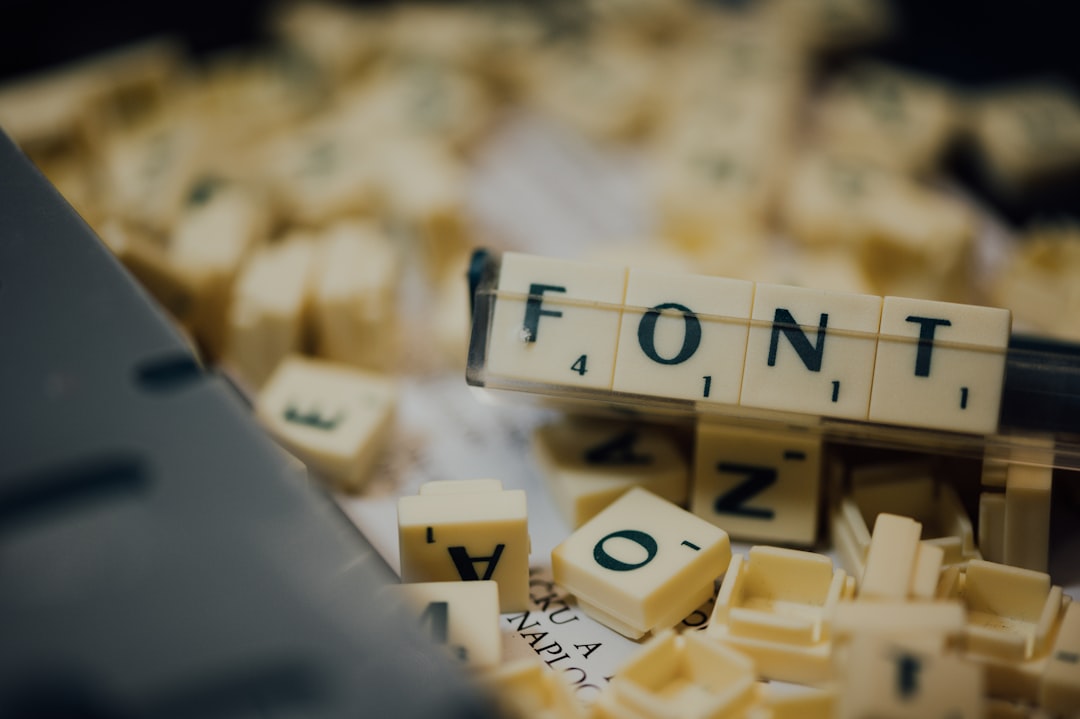
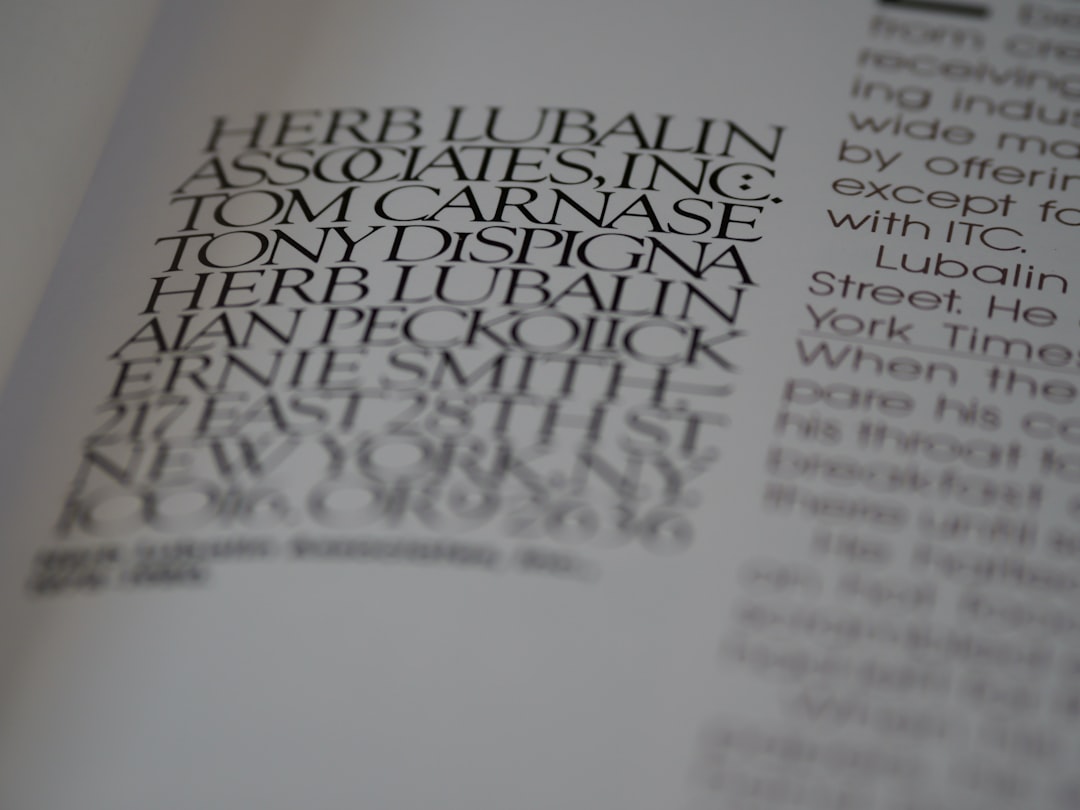
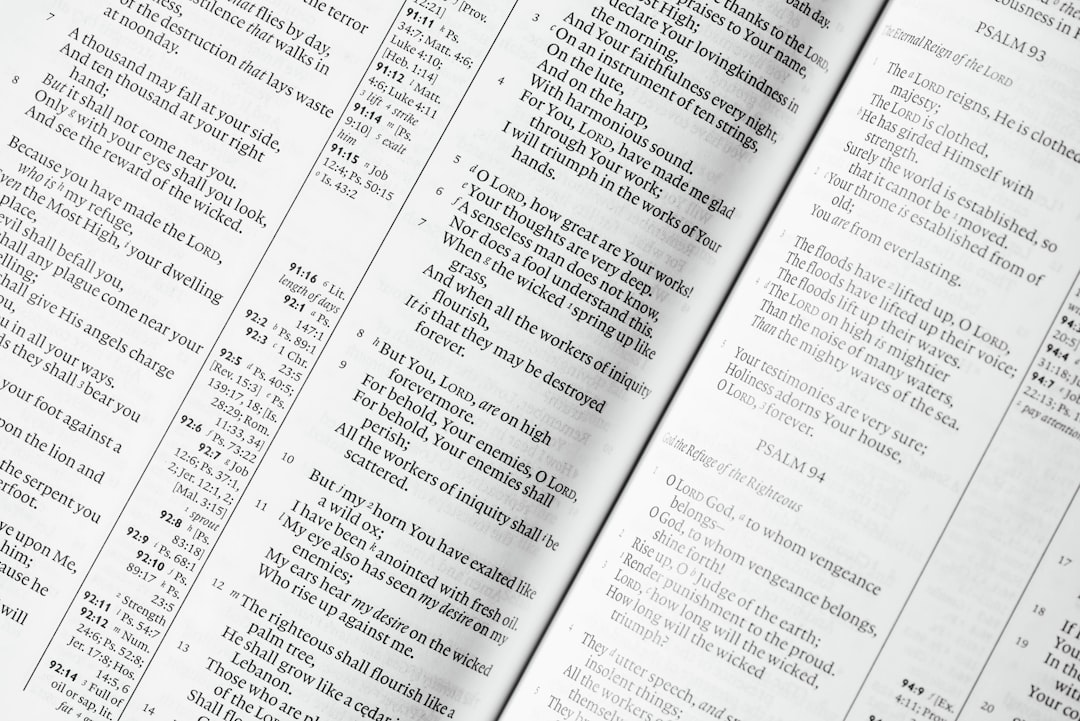
| 웹사이트 | 특징 |
|---|---|
| WhatTheFont | 이미지 기반 폰트 추천 |
| Identifont | 질문 기반 폰트 추천 |
결론
폰트 찾기는 이제 막 시작된 탐험과도 같습니다. 디자인의 중요한 요소인 폰트를 효율적으로 찾는 방법은 우리의 창의성을 더욱 드높이고 디자인 작업을 한층 쉽고 즐겁게 만들어 줍니다. 이제, 여러 웹사이트와 앱을 통해 폰트 찾기를 즐기기 시작해 보세요. 마음에 드는 폰트를 찾은 순간, 여러분의 디자인 작업이 새롭게 찬란히 빛날 것입니다!
자주 묻는 질문
1. 이미지로 폰트를 어떻게 찾나요?
이미지를 업로드할 수 있는 웹사이트에 접속하여 원하는 이미지를 업로드하면, 자동으로 유사한 폰트를 추천해 줍니다.
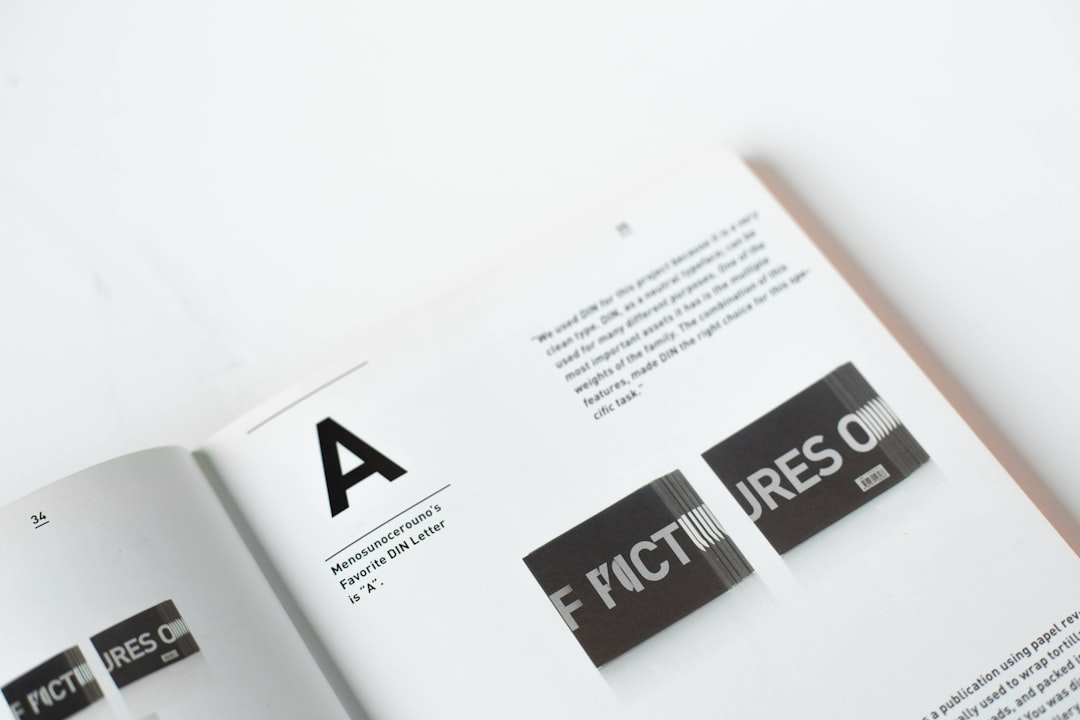
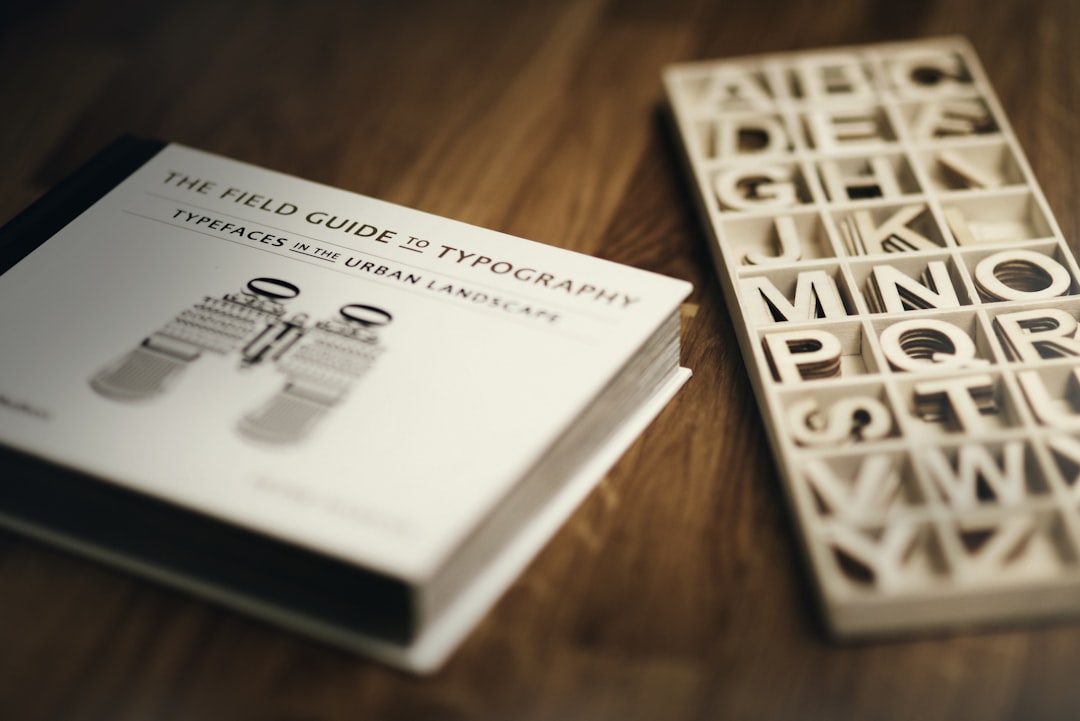
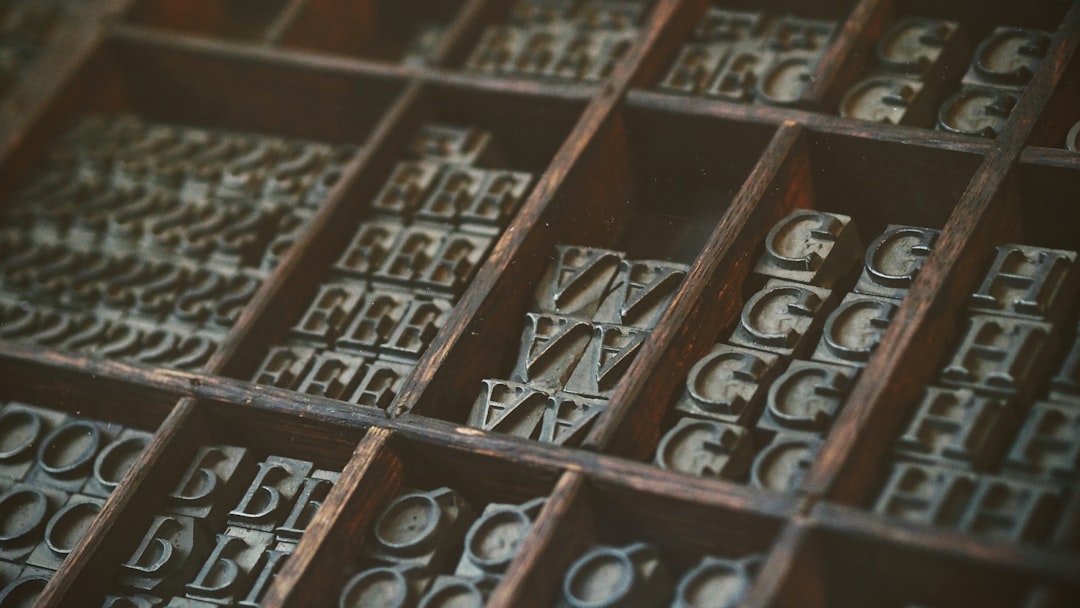
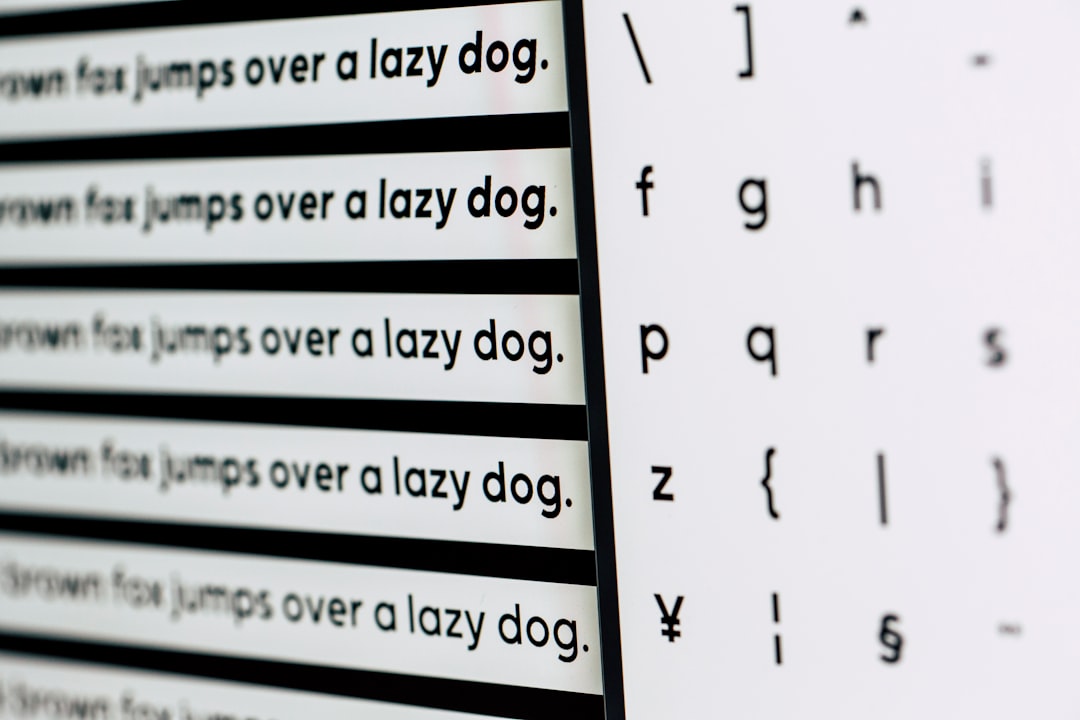
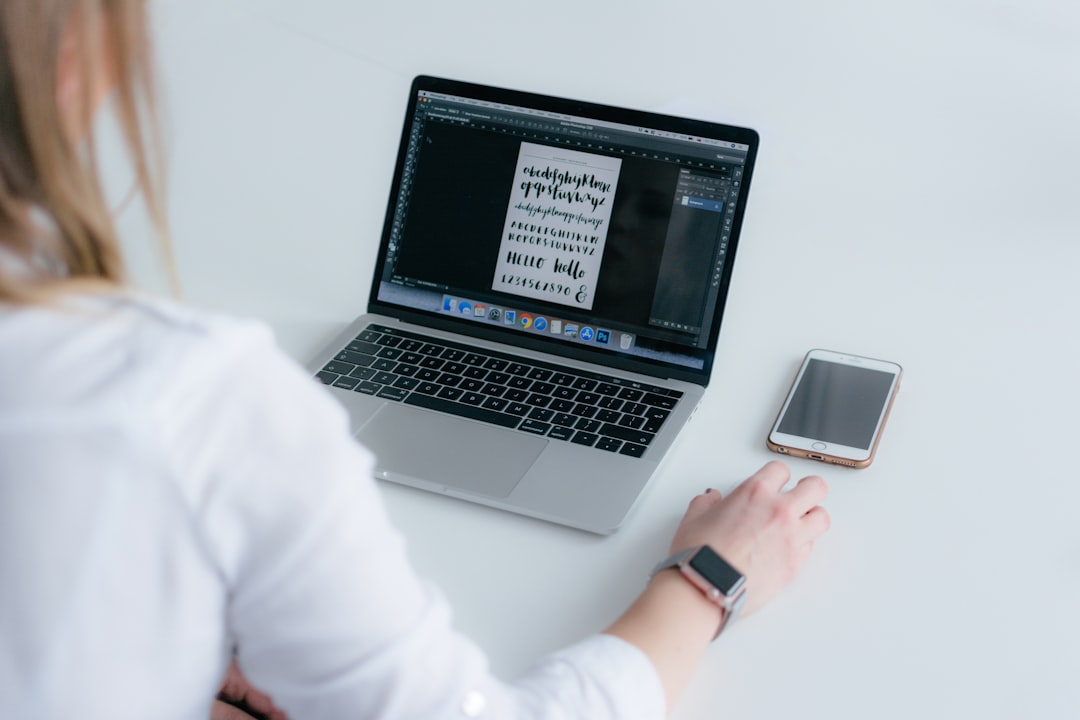
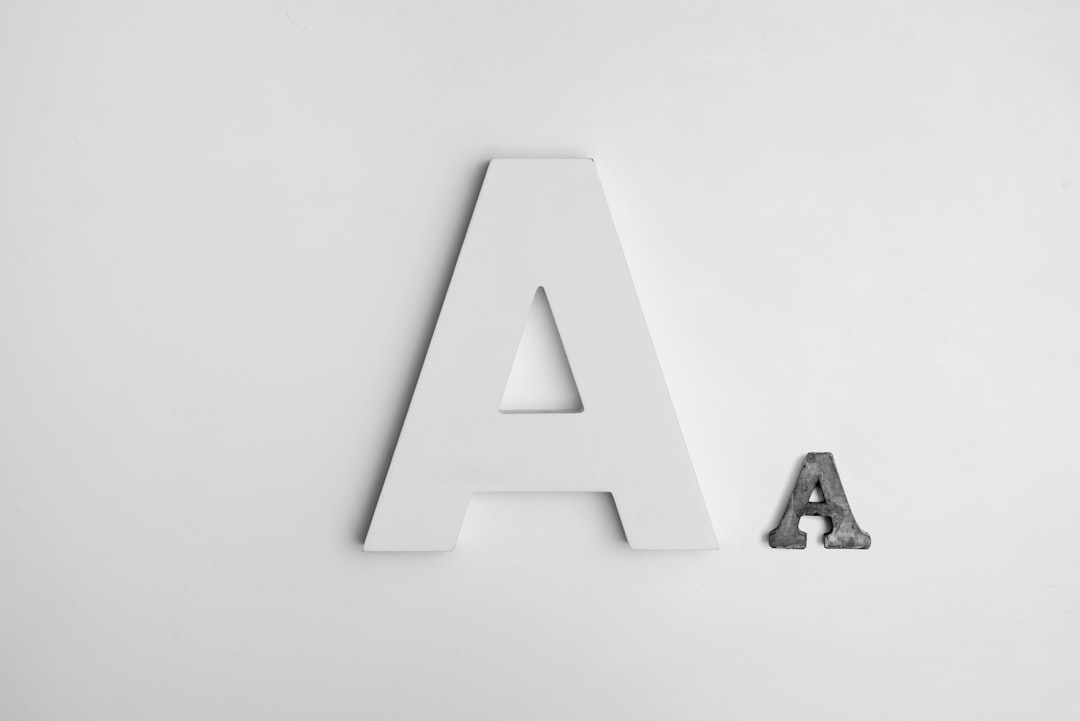
2. 한글 폰트는 어디에서 쉽게 찾을 수 있나요?
한글 폰트는 여러 사이트에서 제공하며, 각기 다른 스타일을 비교해 보면서 선택할 수 있습니다.
3. 영문 폰트 찾기가 어려운 이유는?
영문 폰트는 다양성이 크고, 비슷한 스타일이 많기 때문에 비교적 찾기가 힘들 수 있습니다. 이미지 분석 서비스를 활용하면 도움이 됩니다.